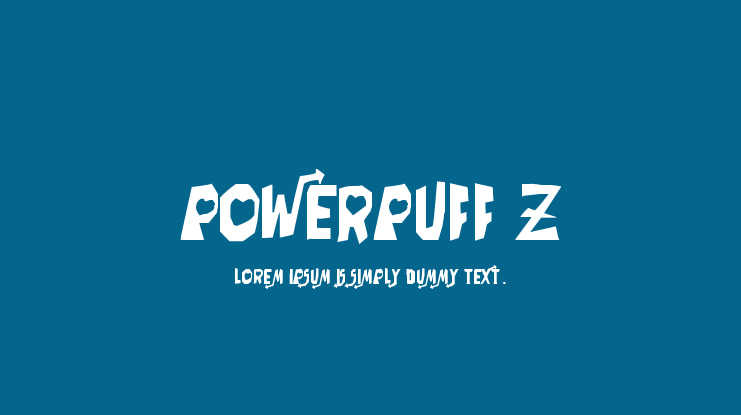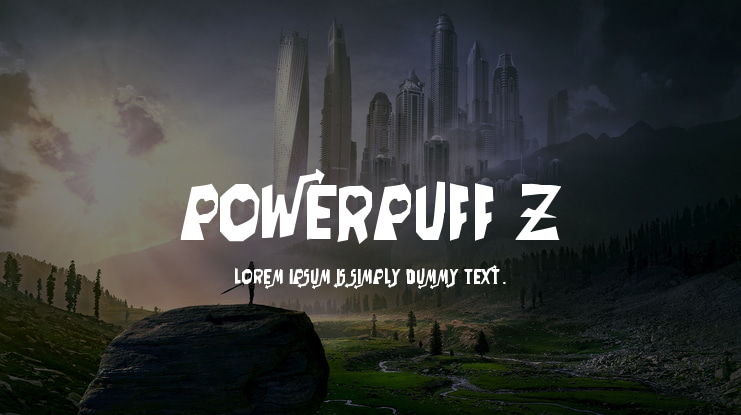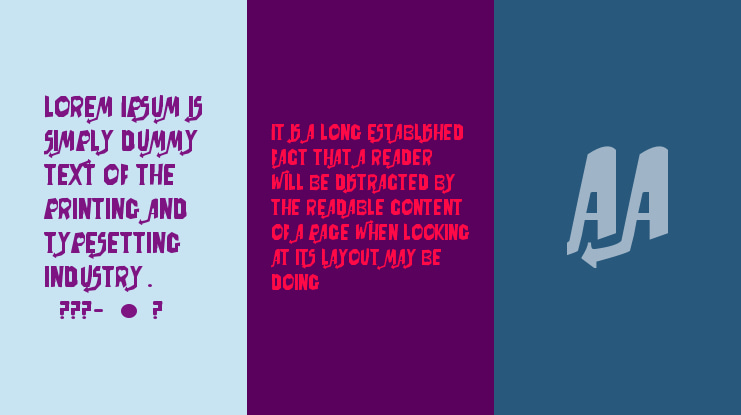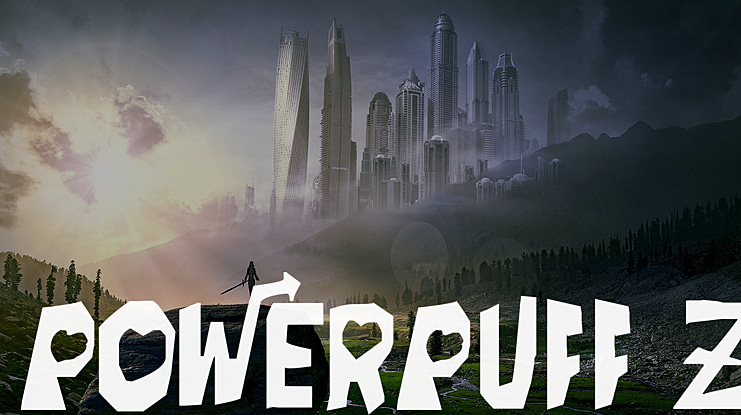
PowerPuff Z Font
PKFS
Versión 4,00 de la Fuente Powerpuff Z. Ahora con mas caracteres! Los números se incluirán en la versión 5,00. Las letras ahora con un retoque mas moderno.
Version 4.00 Of the Font Powerpuff Z. Now with more characters ! The numbers will be included in the 5,00 version. The letters now with a more modern touch.
Exclusive Font for PPGZ Fan / Fuente Exclusica para los Fans de Las Chicas Superpoderosas Z
Demashitaa! PPGZ
Jorge Paulino Dzul Koyoc (PKFS Tipographyc)